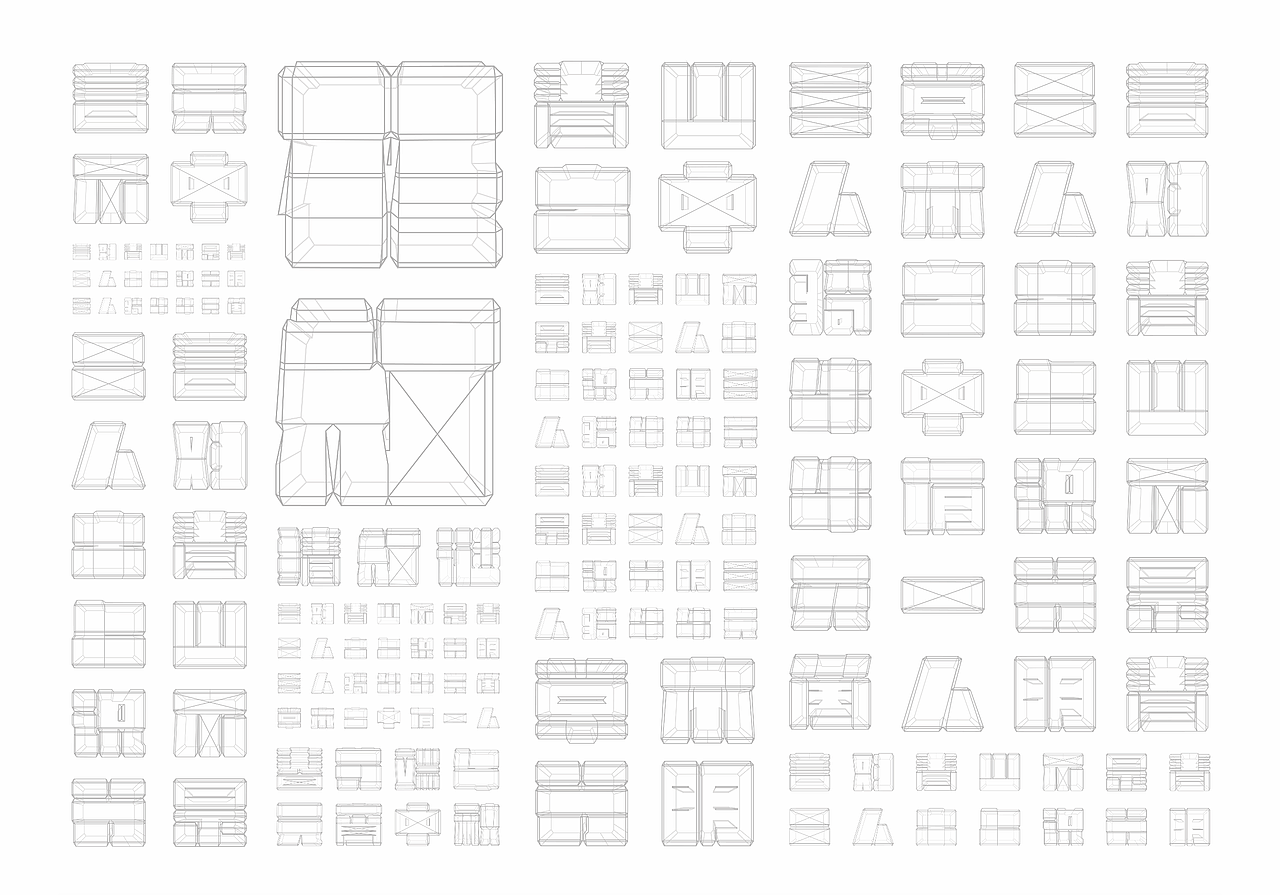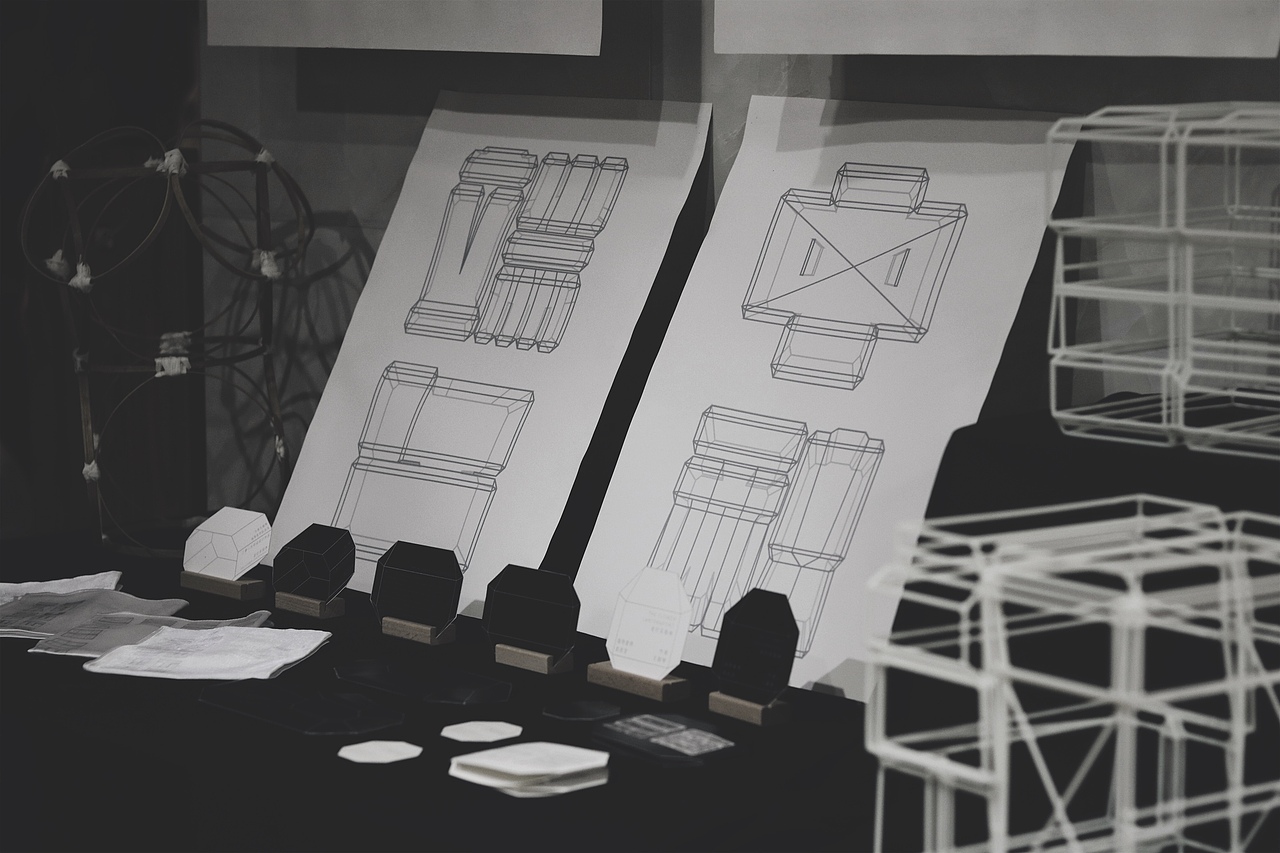
花灯实验体-花灯字体再创作
当下多数传统技艺仍以它们固有的形式存在,我希望借此探索传统文化更多元的应用场景。
至今2000多年的花灯是中国农业时代的文化产物。
它酬神娱人,兼具生活功能与艺术特色。
作品以花灯形态为灵感,探索文字字型、骨架结构、光源明暗的相互作用:
可以是平面或立体装置、可以只有外部轮廓或体现内部骨骼,
重新定义的花灯体没有限定,
变化出无限的想像空间。